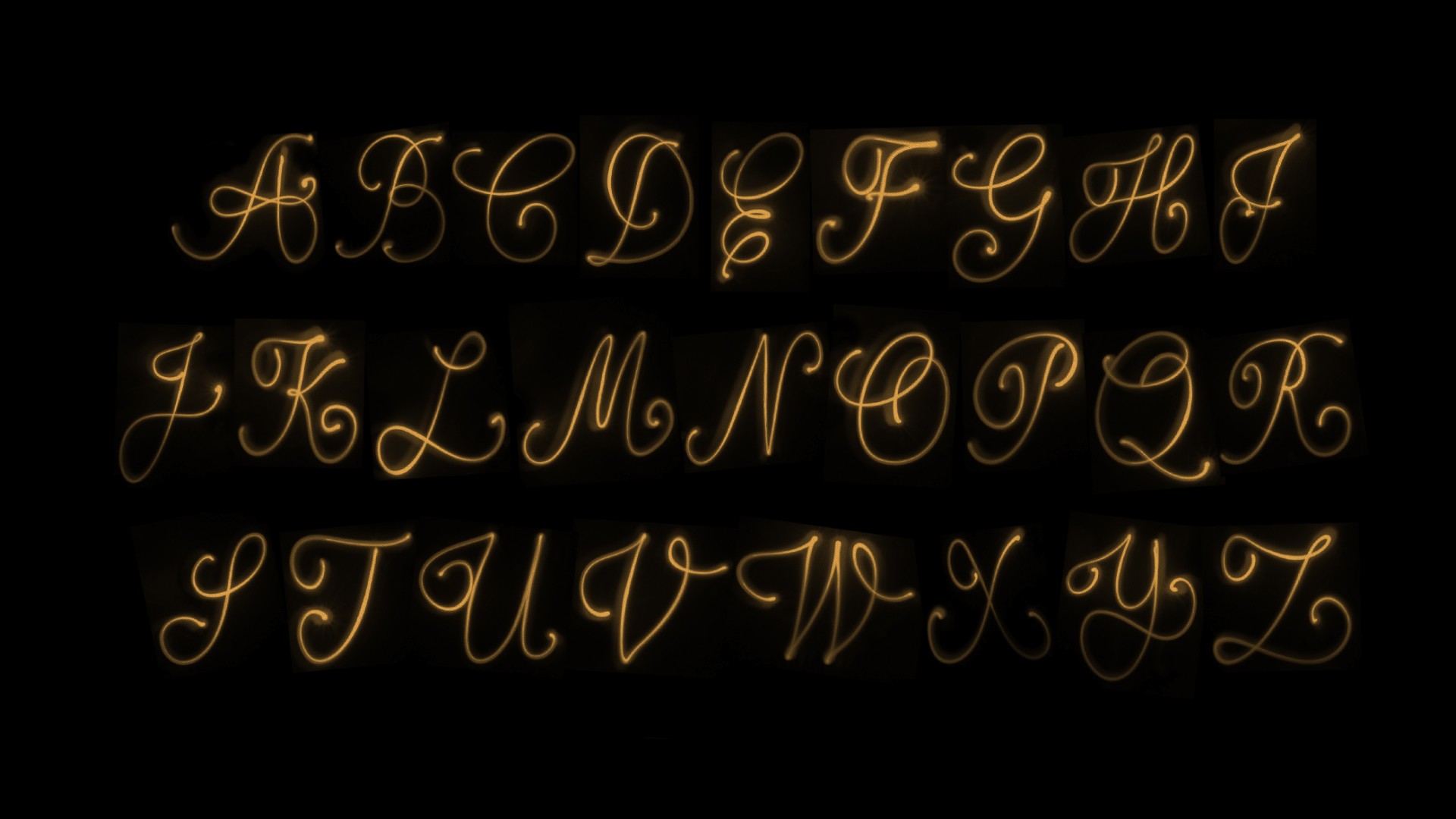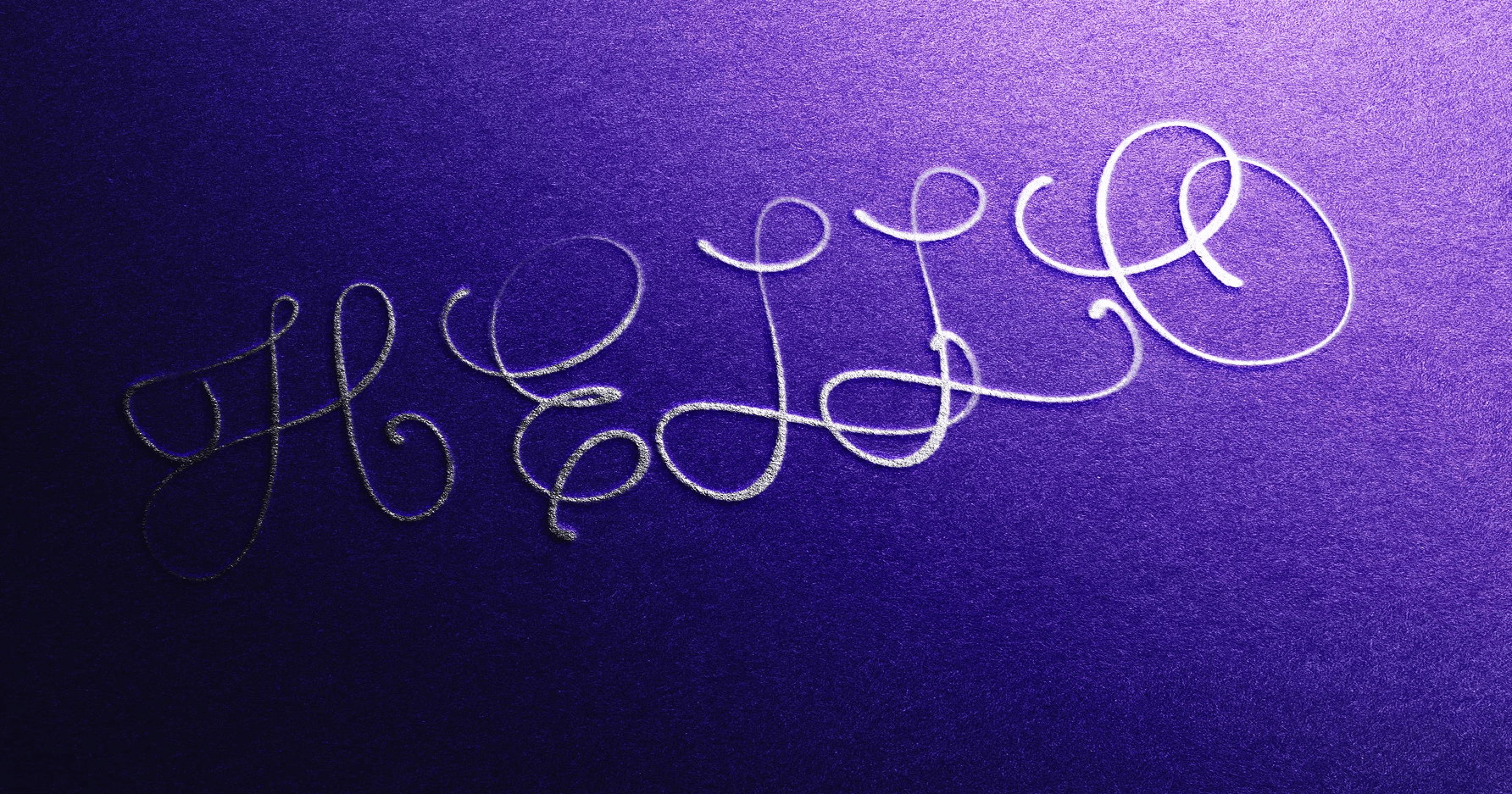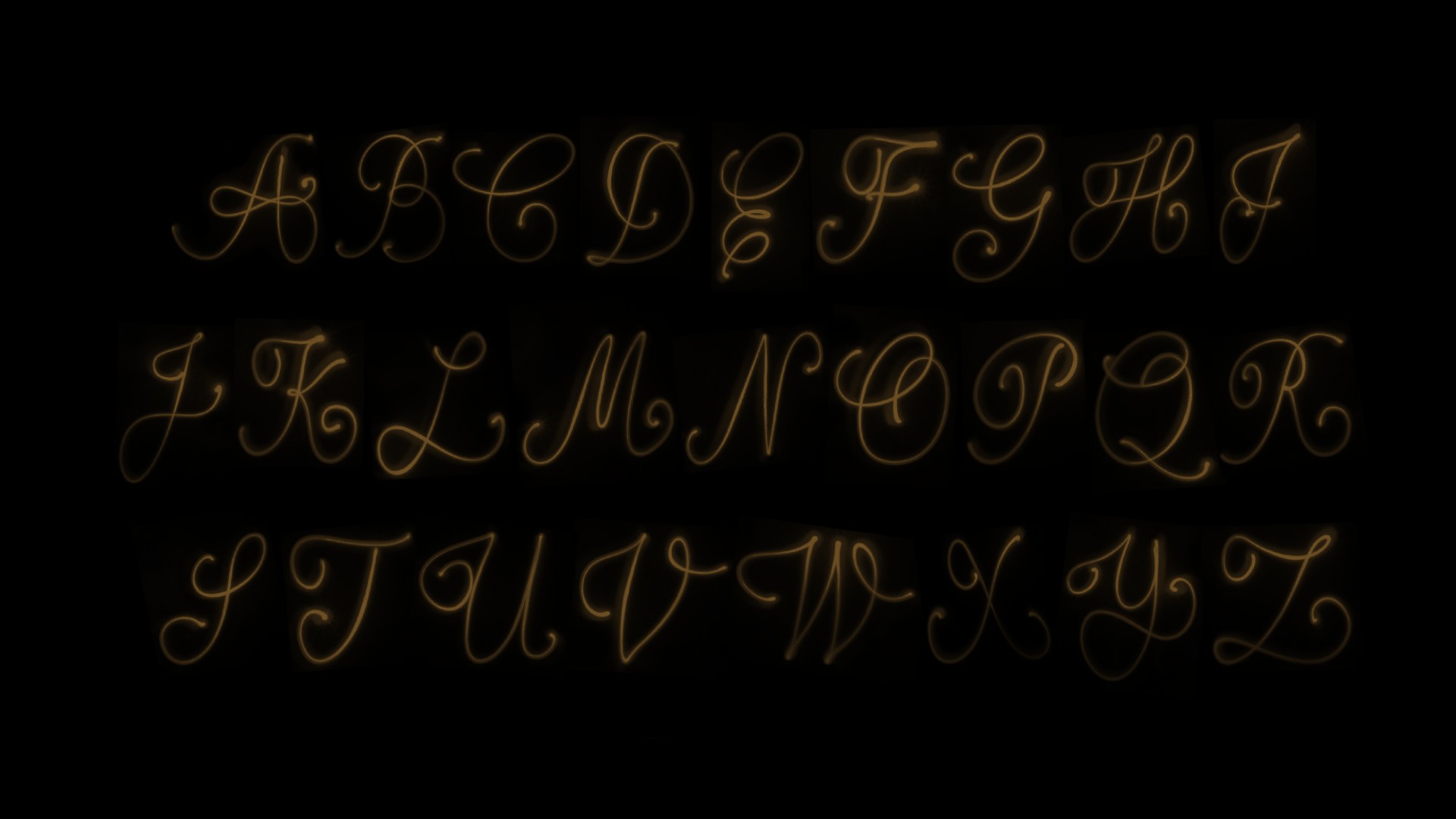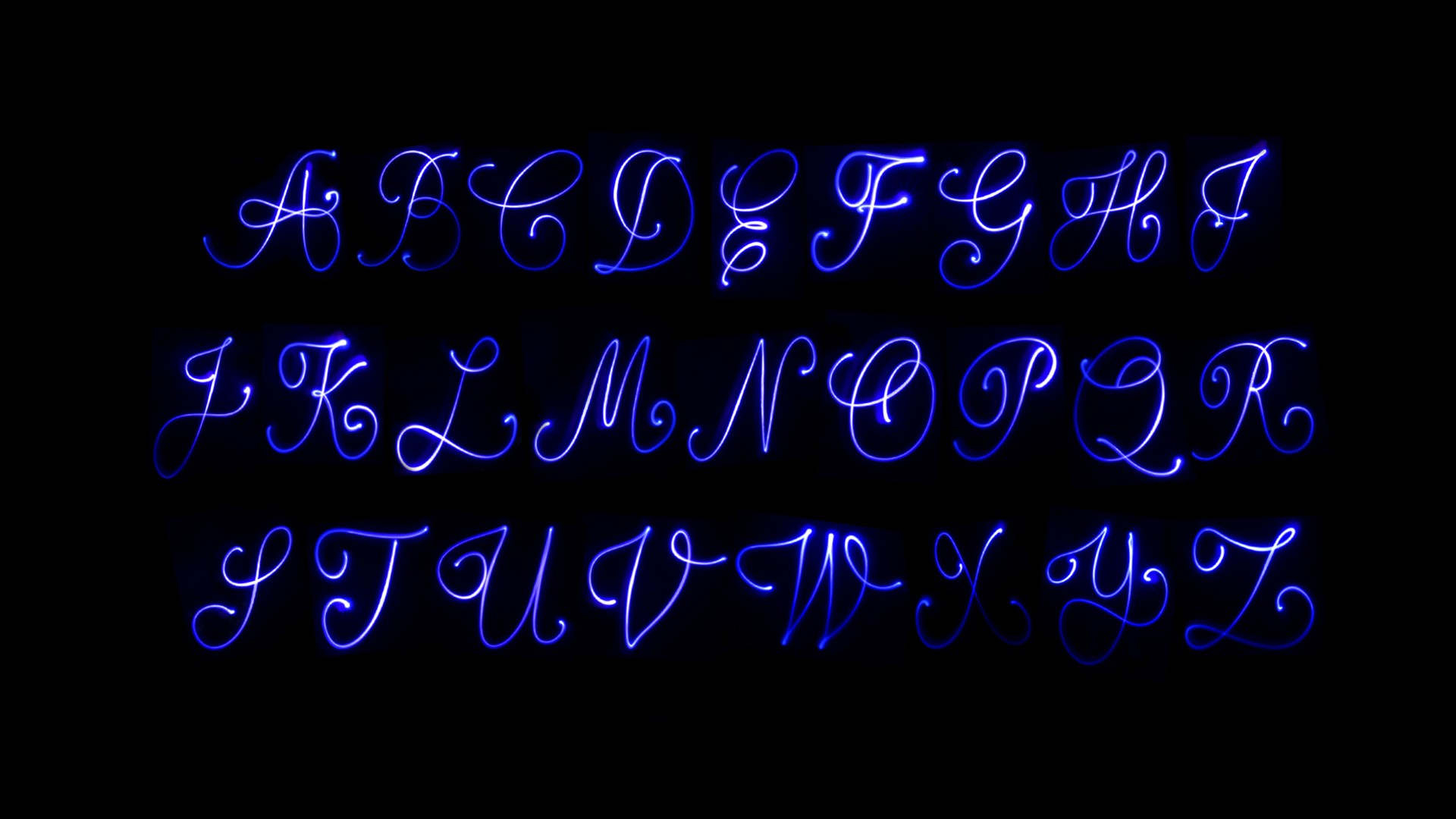
'Blinding Lights' es una tipografía experimental creada con la técnica del light painting, se trata de configurar la cámara réflex de una forma que atrape la luz que entre en el objetivo en un mayor tiempo, tocando la velocidad de obturación (10’’) y la apertura del diafragma (f/20), entonces quien dibuja se queda a oscuras con único punto de luz, consiguiendo este efecto de tipografía retroiluminada.